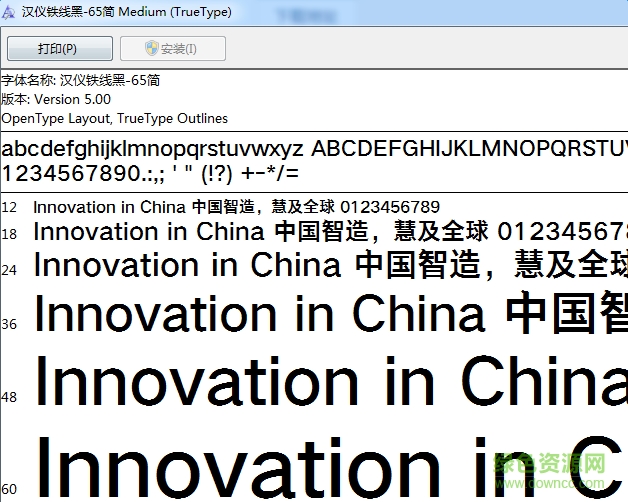
漢儀鐵線黑 65簡 medium字體是漢儀鐵線黑系列字體中的一款,該字體非常有個性,可以廣泛應(yīng)用于廣告設(shè)計(jì)、宣傳海報、ppt、影視制作以及任何使用文字的領(lǐng)域,有需要的朋友可以免費(fèi)下載收藏。
漢儀鐵線黑 65簡 medium字體是一款漢儀字體庫中的個性字體,字型非常大氣,有喜歡的朋友就來綠色資源網(wǎng)下載使用吧!